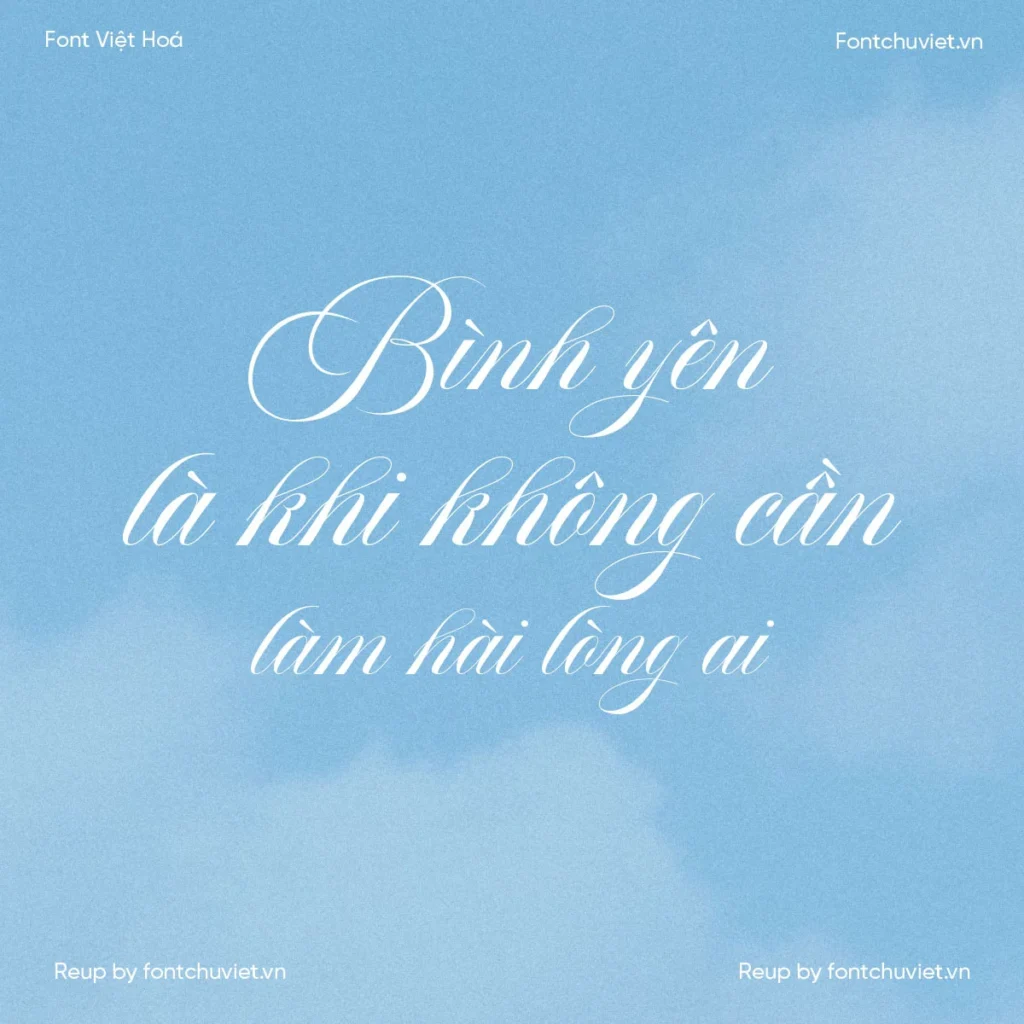
Font VL Aston Script – Font Việt hoá là một trong những font viết tay đẹp và phổ biến hiện nay. Với nét đậm và đẹp, font này là lựa chọn hoàn hảo cho thiết kế thiệp cưới, thiệp mời và các sản phẩm khác.
Font VL Aston Script – Font Việt hoá: Đặc điểm và ứng dụng
Font VL Aston Script – Font Việt hoá có nhiều đặc điểm nổi bật như nét đậm, đẹp và dễ đọc. Font này thường được sử dụng trong thiết kế thiệp cưới, thiệp mời và các sản phẩm khác.
Lợi ích của Font VL Aston Script – Font Việt hoá
Font VL Aston Script – Font Việt hoá mang lại nhiều lợi ích cho người dùng như:
- Tăng tính chuyên nghiệp cho thiết kế
- Cung cấp nhiều lựa chọn cho thiết kế
- Dễ đọc và đẹp
Sai lầm khi sử dụng Font VL Aston Script – Font Việt hoá
Để sử dụng Font VL Aston Script – Font Việt hoá hiệu quả, bạn nên tránh một số sai lầm như:
- Sử dụng font không phù hợp
- Không sử dụng font một cách linh hoạt
Font VL Aston Script – Font Việt hoá là một lựa chọn hoàn hảo cho thiết kế thiệp cưới, thiệp mời và các sản phẩm khác. Để sử dụng font này hiệu quả, bạn nên cài đặt font đúng cách, sử dụng font một cách linh hoạt và tránh các sai lầm khi sử dụng font.